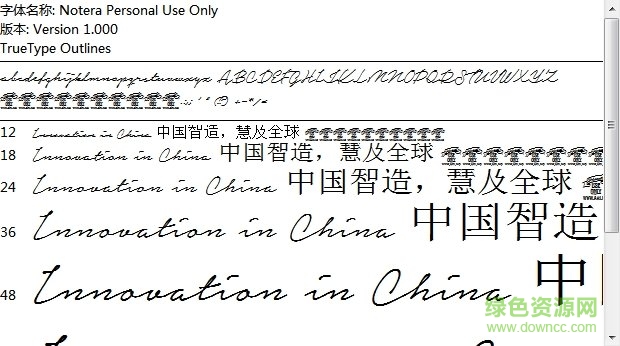
notera是一款連筆英文字體,造型大氣沉穩(wěn),很有英文手寫字體的連貫方格,十分流暢大方,喜歡的朋友快來綠色資源網(wǎng)體驗(yàn)吧!
notera英文字體有著連筆流利的干凈特色,中文字體上并無出色體驗(yàn),適合于一些英文句子的修飾和美化,給人干練簡(jiǎn)潔的舒適體驗(yàn)!